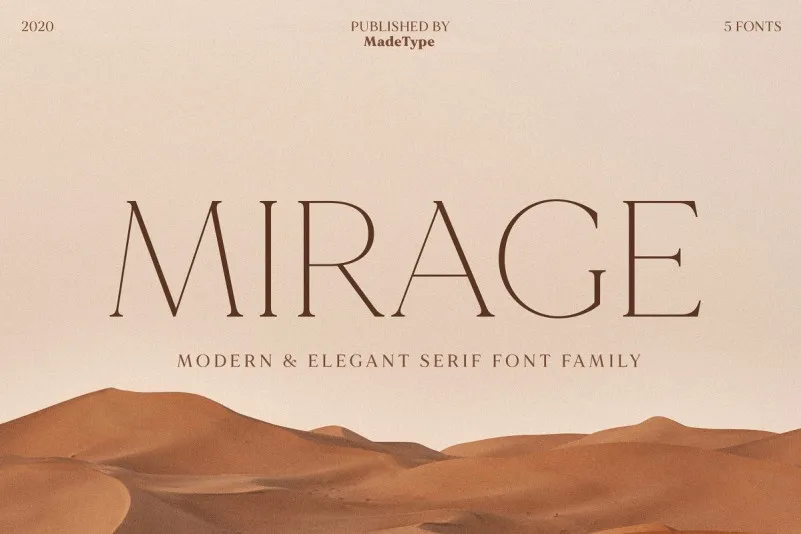
A MADE Mirage Serif é uma nova adição para os designers que buscam uma tipografia sofisticada e elegante. Esta família de fontes serif apresenta um estilo moderno e refinado, perfeitamente compatível com san serifs contemporâneos, scripts fluidos ou mesmo se destacando sozinha como fonte de cabeçalho ou layout editorial. A MADE Mirage está disponível para aqueles que desejam uma aparência luxuosa, minimalista e moderna em seus projetos de design. Esta família de fontes é adequada para uma variedade de aplicações, incluindo moda, revistas, logomarcas, identidades criativas, fotografia, convites, casamentos, citações, cabeçalhos de blog, postais, flyers, livros e websites. A MADE Mirage está aqui para tornar seus projetos ainda mais profissionais e atraentes com um design moderno e elegante.